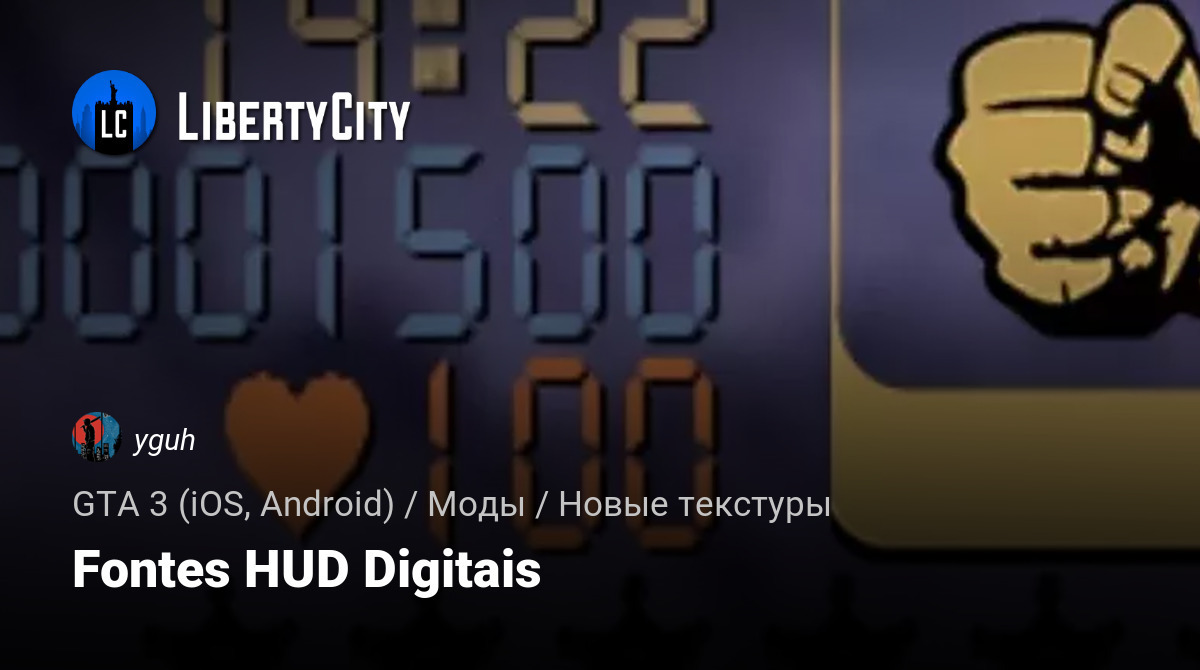
Цифровые HUD шрифты
Этот мод изменяет все цифры в игре, но отображается только при сохранении игры, в миссиях с ограничением по времени или для просмотра хаба, не меняет много вещей.
• Текстуры взяты из GTA FW
• Красивые цифры
Fontes HUD Digitais
Esse mod modifica todos os números do jogo, mais apenas aparace na hora de salvar o jogo, missão com tempo ou para olha o hub, não muda muita coisa.
• As texturas foram tiradas do GTA FW
• Números mais bonito